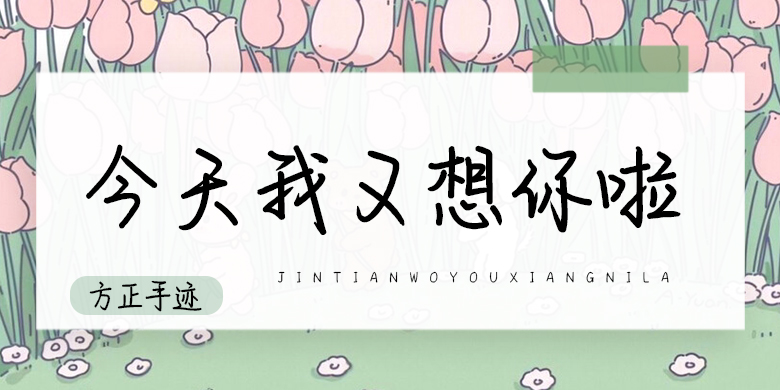
方正手迹-今天我又想你啦
字体品牌: 方正手迹 设计师:王航 字体分类:常规书写·硬笔 字体属性:精品字 字符集:简繁扩展(GBK) 发布时间: 2021
今天我又想你了这款字体线条圆润舒缓,笔画遒劲灵动,加以适当的连笔,显得张弛有度,优雅洒脱,是一款优秀中文美术字体。适用于文艺类的书刊、品牌广告和产品包装设计以及社交网络的个性化用字。